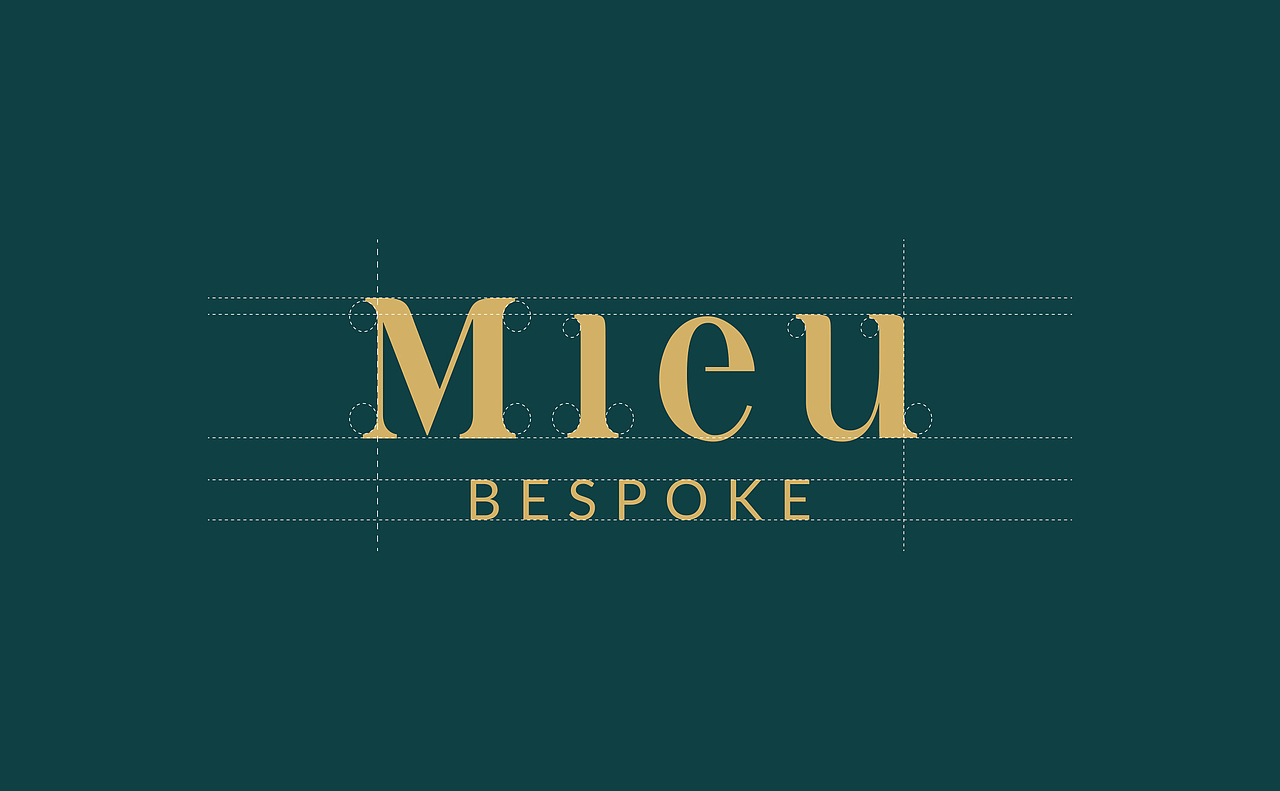
Mieu Eyewear Bespoke
Mieu Eyewear Bespoke 是Mieu Eyewear的私人定制眼镜业务,单价在RMB4000~RMB10000之间,每一付眼镜都是量身定做的唯一的款型。用户是30-45岁左右事业有成的中产男性。
整体风格关键词:精致、奢侈、华美。委托方希望设计师从希腊经典时期或者洛可可到文艺复兴时期寻找装饰元素与风格灵感。Bespoke仍是Mieu Eyewear的一部分,所以视觉上需要以Mieu的主品牌图形logo为主,但需要更加华丽和精致。
以抽象的猫头鹰符号作为品牌的象征与标识顶部的装饰。猫头鹰是古希腊文化中智慧的象征。猫头鹰头顶的皇冠代表品牌的高端定位以及对顶级品质的追求,也象征着品牌的独一无二。
标识整体的纹饰采用欧洲文艺复兴时期与希腊经典时期相结合的风格特点,体现了品牌与产品的艺术品位。
以“μ”与“β”符号作为标识的主体与视觉中心,体现了Mieu Bespoke与主品牌Mieu Eyewear的紧密联系。
主品牌logo,相比原有品牌,这次的定制品牌设计更加成熟与男性化。
欧洲各个时期的艺术代表元素与风格
logo演变完善过程
字体部分继承主品牌logo特点
标识整体的纹饰采用欧洲文艺复兴时期与希腊经典时期相结合的风格特点,体现了品牌与产品的艺术品位。
logo产品应用
提案中的其他设计思路